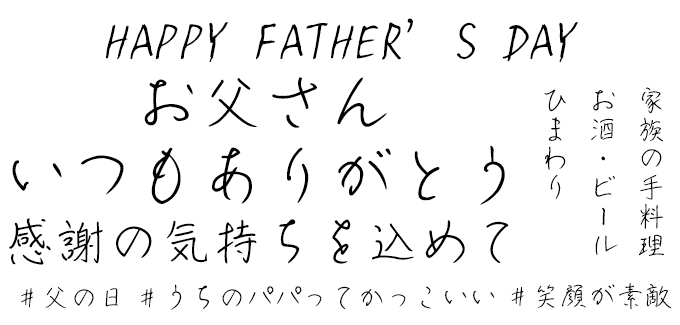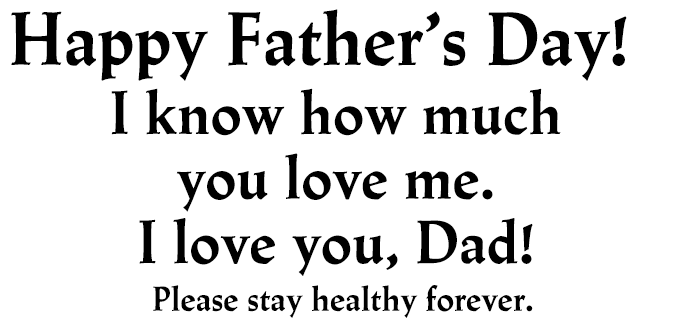
父の日に合うフォント 特化型 目的別フォントガイド
使用フォント:DSあかり
父の日に合うフォント:特化型 目的別フォントガイド #008
今回は父の日に合うフォント。日々フォントのことばかり考えている当店スタッフが直感的に選んだフォントをご紹介します。
父の日に合うフォントをスタッフが選びました
父の日に合うフォント #1 パンダベーカリー
パンダベーカリー【鈴木メモ】
手作り感のある可愛らしさが魅力、太めのゴシックベースのデザイン書体。どっしりとした安定感と親しみやすさがお父さんの印象ともマッチする書体です。
父の日に合うフォント #2 TAかいと
TAかいと【スキルインフォメーションズ】
普段は仕事で外出する事が多いため、母と比べて会話が少なくなりがちですが、家族を思う気持ちや愛情は誰よりも深い父。思春期の子供が日頃の感謝の気持ちを伝えるために頑張って書いた手紙の手書き文字はこんな感じかな?と思いました。けして奇麗な字ではないけど手紙にしたためた「ありがとう」には愛情と照れる気持ちがこもっていると思います。
父の日に合うフォント #3 筆技名人フォント 遊月体 (MNT/MNO遊月体)
筆技名人フォント 遊月体 (MNT/MNO遊月体)【ミーネット】
クレオンで書いたような手書き文字は、温かく優しい印象なので、日ごろ素直に伝える事のできない、父への感謝の気持ちを表す時に最適です。
父の日に合うフォント #4 さむらい
さむらい【白舟書体】
連綿線やはねを多用し切れ味鋭い書体で、かつて畏怖の対象となっていた父親(子からみて1親等の親族で男性の親)像が表現できます。
父の日に合うフォント #5 弘道軒清朝体/弘道軒清朝体現代版/復刻版Pro
弘道軒清朝体/弘道軒清朝体現代版/復刻版Pro【イワタ書体ライブラリー】
明治20年代にかけて一世を風靡した日本で一番古い部類の金属活字楷書体「弘道軒清朝体活字」をベースにデジタルフォント化した鋭角なシルエットを持つ独特な書体は、威厳ある父親のイメージにぴったりです。
父の日に合うフォント #6 横丁&鍛所 あまからフォント
横丁&鍛所 あまからフォント 【六葉情報】
THE・日本の父にピッタリくる和テイストの筆文字。極太の力強くしっかりメッセージが伝わります。
父の日に合うフォント #7 DS照和80
DS照和80【七種泰史/デザインシグナル】
世のお父さんが懐かしさを感じるであろう1970年から1980年代をイメージした手描き風書体。お父さんのイメージにもぴったり合うデザインフォントです。
父の日に合うフォント #8 ITC Franklin Gothic™ Pro Demi
ITC Franklin Gothic™ Pro Demi【ITC】
古風で粗削りな男らしいサンセリフ。父親の力強さを表現するのに相応しい書体です。
父の日に合うフォント #9 Linotype Trajanus™ Pro Bold
Linotype Trajanus™ Pro Bold【Linotype】
父親が放つ格式と威厳、堂々とした佇まいを表現するのにピッタリのフォントです。
父の日に合うフォント #10 Renju Regular
Renju Regular【INGRAM】
欧文フォントながらカナ(かな)を収録。スチームパンクなデザインがお父さんの遊び心を思わせます。